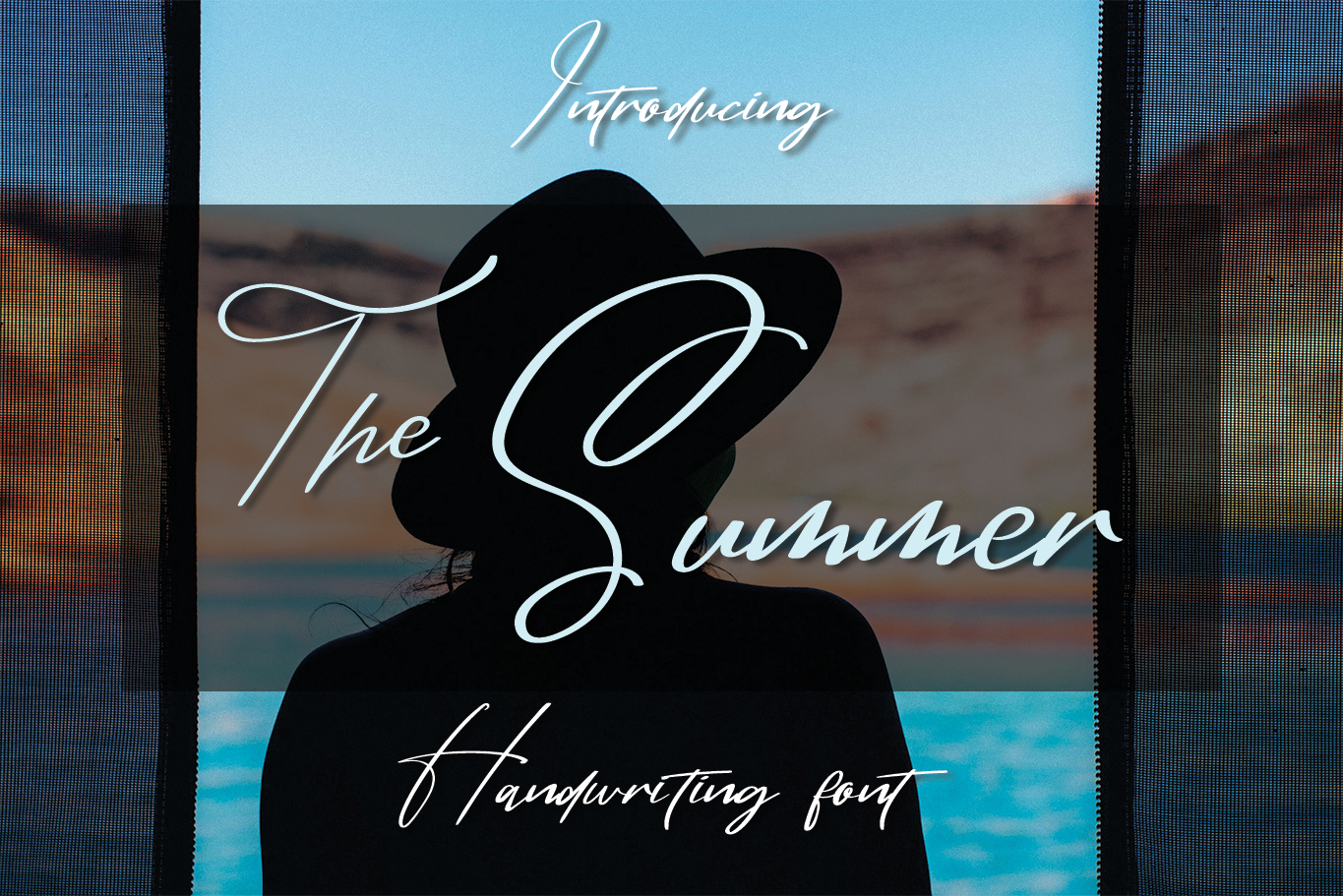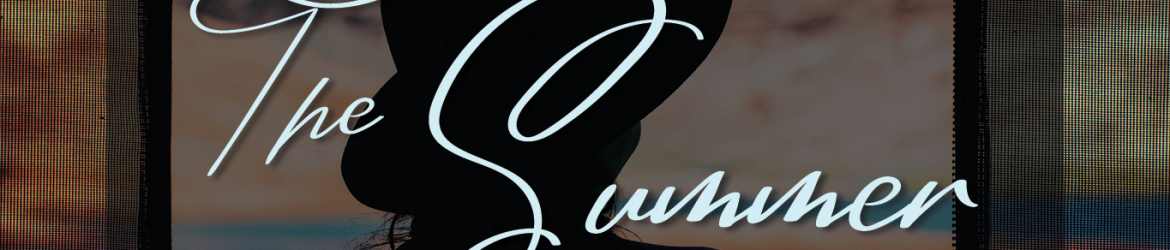
The Summer Font – Download Grátis
A fonte “The Summer” é uma elegante e fluída escrita à mão perfeita para quem busca um toque delicado e romântico em seus projetos de design. Essa fonte cheia de vida é especialmente perfeita para criar cartões de casamento, convites ou qualquer outro tipo de projeto que possa requerer uma sensação personalizada e delicada. Com seu charme suave e sua disposição entrelincada ao longo do texto, “The Summer” criará um ambiente acolhedor e natural em seus projetos, tornando o design mais especial e emocionante para os momentos mais importantes da vida. Inspirado pelo calor e pela luminosa alegria do verão, este design de escrita à mão se adapta perfeitamente para qualquer projeto que deseje trazer uma atmosfera romântica e pessoal ao seu trabalho.